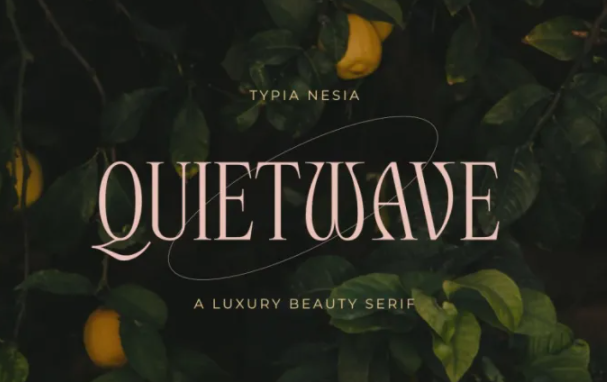
[Creativemarket] Quitewave Font (2021)
Quietwave - роскошный красивый выразительный шрифт - классический элегантный фантазийный шрифт
В комплект Quietwave входит несколько альтернатив и лигатур, поэтому вы можете комбинировать их, чтобы создать идеальный шрифтовой дизайн. Он идеально подходит для ваших будущих проектов. Например, роскошный логотип и брендинг, стильный редакционный дизайн, женский журнал, косметический бренд, модный промоушен, брендинг художественной галереи, музея, исторических архитектурных сооружений, брендинг бутика, дизайн канцелярских принадлежностей, дизайн блога, современный рекламный дизайн, пригласительная открытка, художественная цитата, домашний декор, название книги/обложки, специальные мероприятия и многое другое.